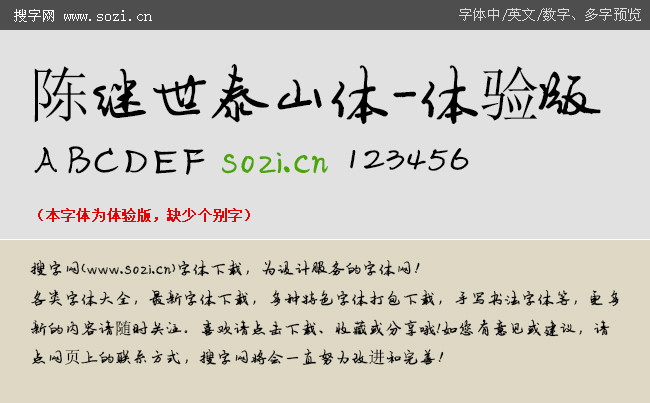
陳繼世泰山體-體驗版
搜字網(wǎng)給大家提供一款陳繼世泰山體-體驗版中文字體下載,陳繼世泰山體體驗版是一款硬筆行楷字體,該字體字重心微微下移,給人以沉穩(wěn)的感覺,字形清秀靚麗,閱讀流暢,適合應(yīng)用于藝術(shù)設(shè)計、平面宣傳設(shè)計、網(wǎng)頁設(shè)計等應(yīng)用。(本字體為個人非商用體驗版,如需要商用請購買正式版版權(quán))